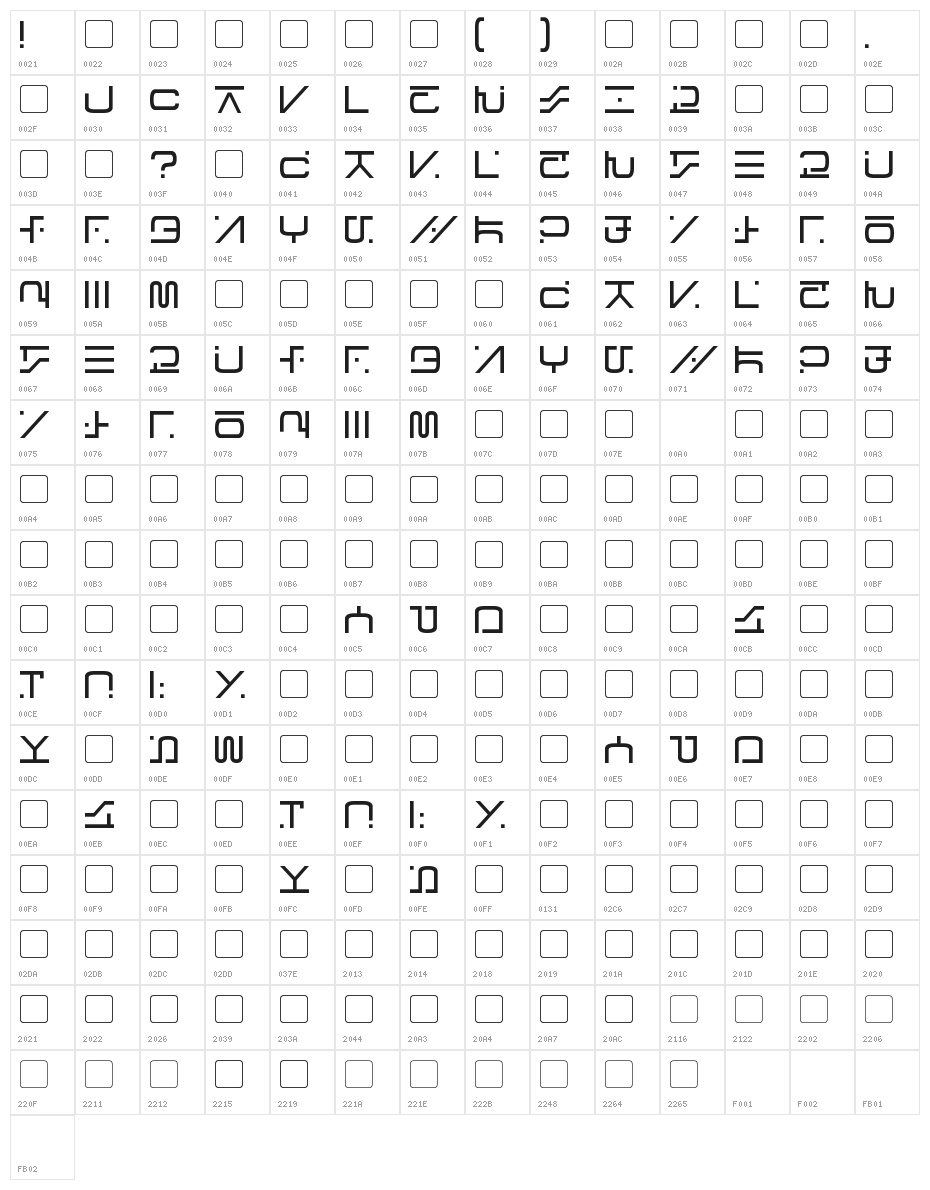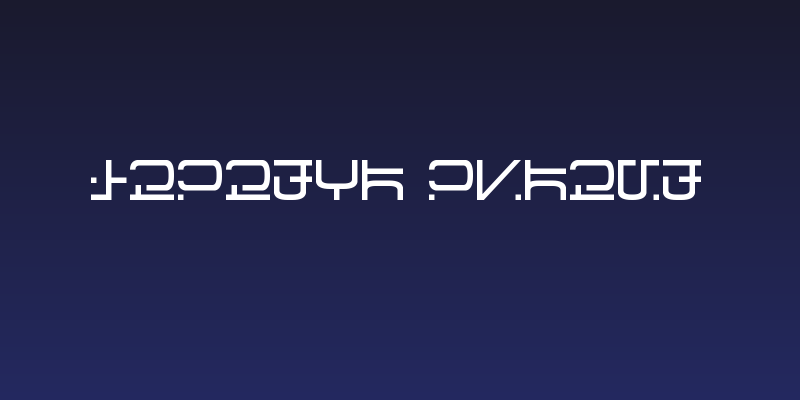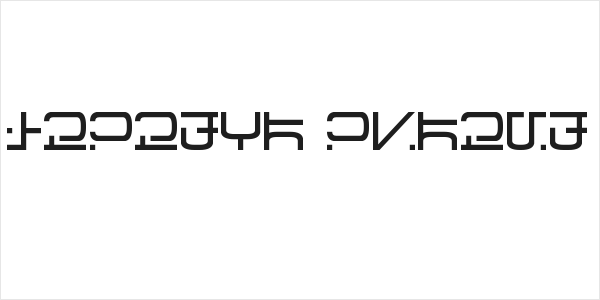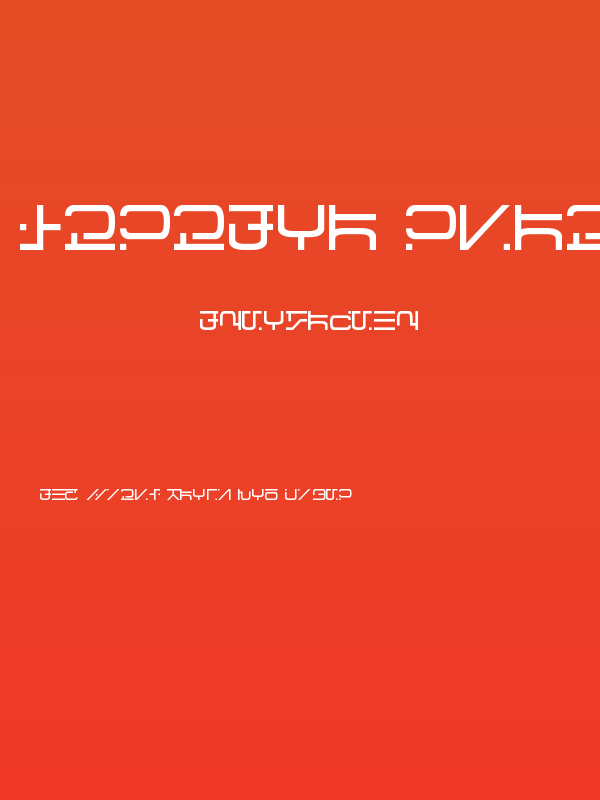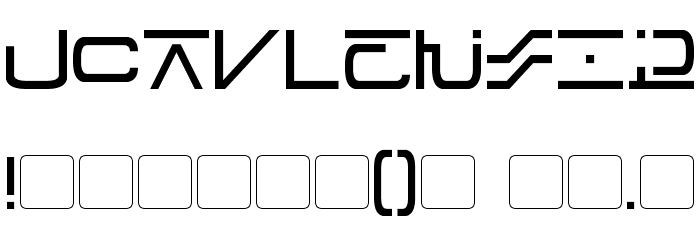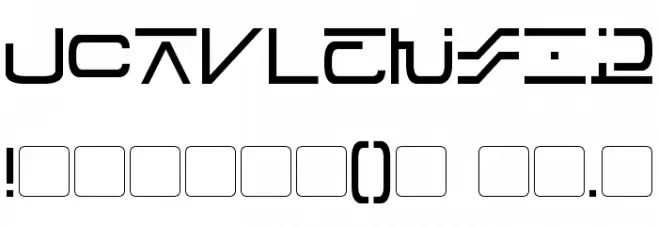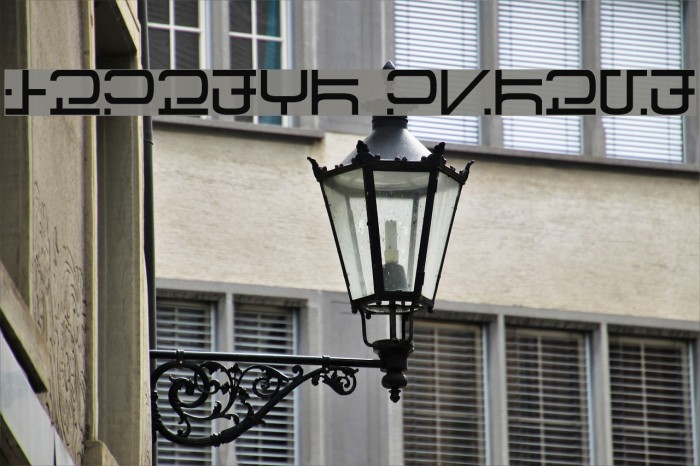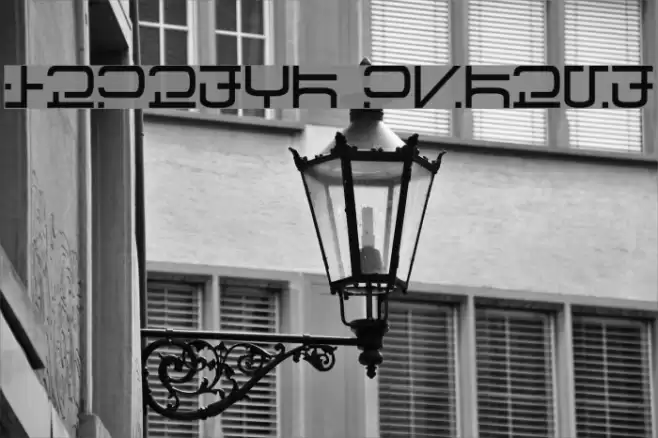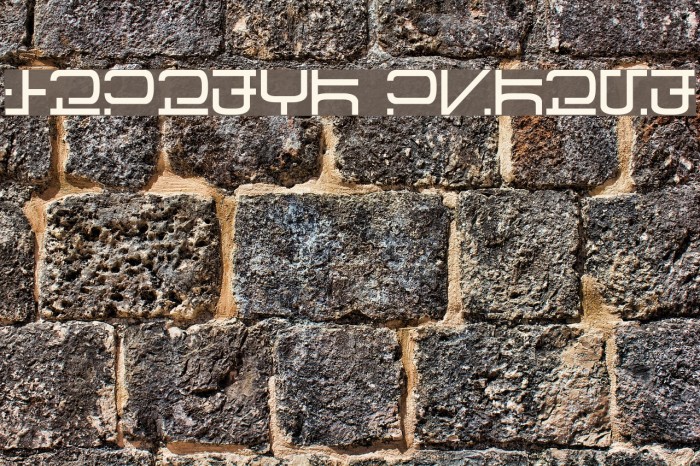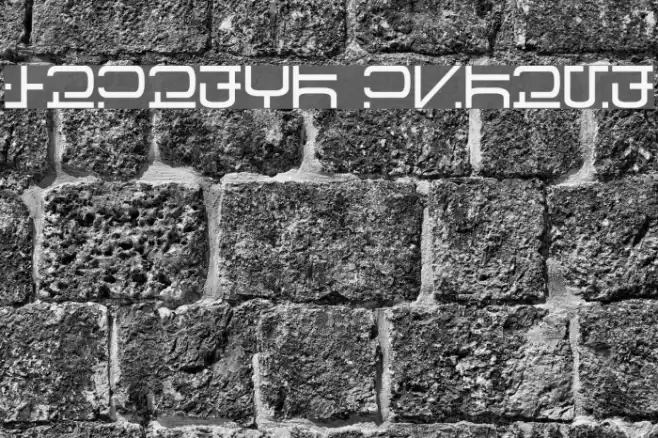
Visitor Script Font
| Категория | Script |
| Общий стиль | Futuristic |
| Область применения | Logos, Headlines, Digital Interfaces |
| Рекомендуемые проекты | Ideal for technology branding, sci-fi movie posters, video game interfaces, and digital art projects. |